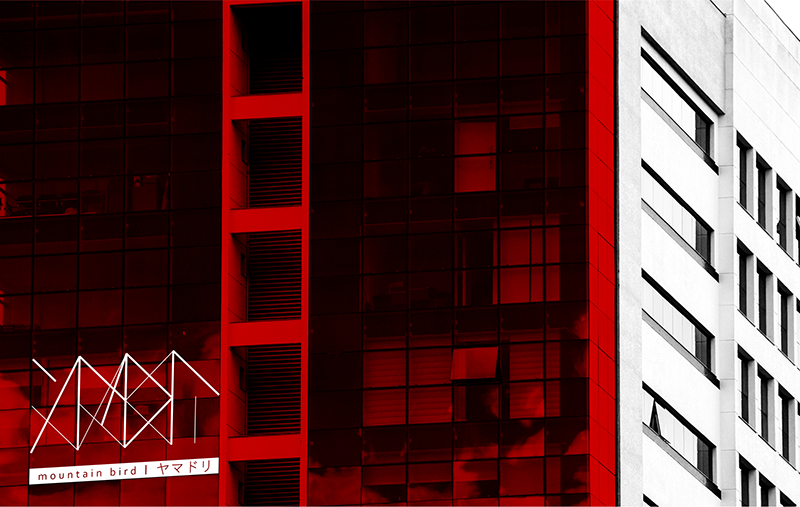
Fonte: AZO Vers�o: .2 Cria��o: Thiago Poltronieri Alves Ol� :) Estou feliz em dividir com voc� minha nova tipografia. Criei ela por divers�o, como na �poca de escola, quando eu criava alfabetos alternativos para conversar durante a aula haha. Essa foi uma mem�ria importante para a cria��o dela :) Nos �ltimo tr�s anos, venho consumindo muito conte�do de fic��o espacial e cyberpunk. Essas refer�ncias come�aram a se tornar prefer�ncia, e na busca por mais conte�do, tive a falsa sensa��o de que j� tinha visto tudo, muita coisa se repetindo. Claro que isso � um engano e obviamente existe outras fontes de consumo que ainda n�o explorei, mas isso � outra hist�ria. Essa falsa sensa��o de fim, me motivou a criar algo que representa-se um resumo de tudo que vi at� aqui. No ano de 2018 flertei com os glifos, alfabeto carbon�rio, cifra de C�sar e Vigen�re, ent�o percebi que a criptografia era muito legal. Tudo isso serviu como inspira��o para a a criar essa tipografia. Divers�o, fic��o, criptografia e mist�rio. Por fim, queria criar uma fonte que escondesse uma mensagem na frente de todos, sem esconder nada de ningu�m. Obrigado pela sua aten��o :) ps: Eu estou usando um software com recursos limitados para a cria��o dos caracteres. Ele me permite desenvolver letras, n�meros e alguns s�mbolos especiais, contudo, me impede de desenvolver acentos, caracteres mais complexos e ligaduras. Me desculpe :/ |